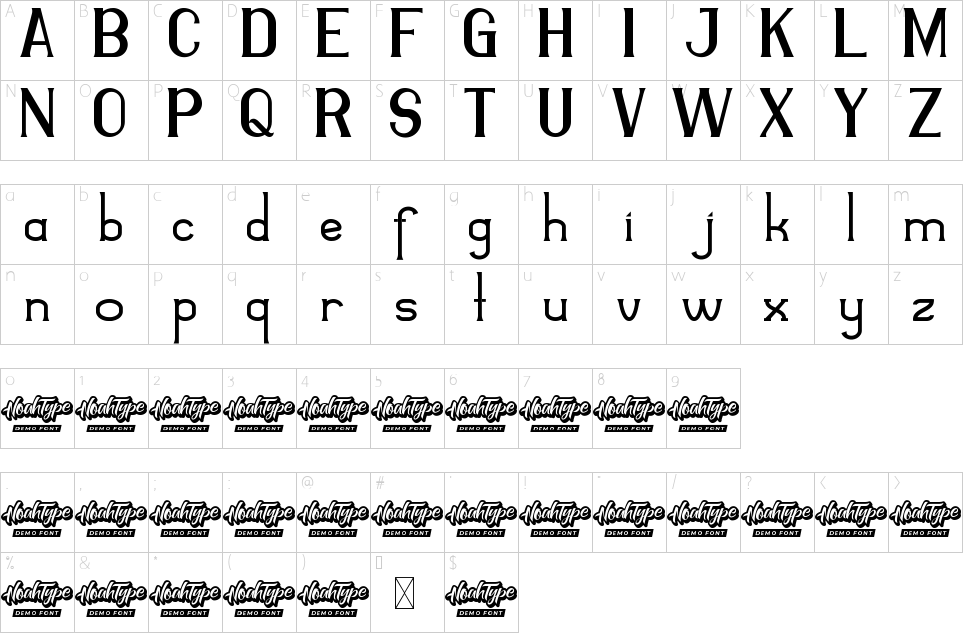
A Monster Mosha Font é uma elegante e divertida opção para quem busca um estilo único e vibrante para seus projetos. Ela foi criada pelo designer NoahType e, embora o nome não seja mencionado na descrição original, já foi baixada por 1.284 usuários. Esta fonte é perfeita para aqueles que buscam uma combinação única de seriedade e humor, sejam eles designers, profissionais de marketing ou criativos em geral. Com um design que mescla linhas fortes e traços delicados, a Monster Mosha é uma escolha adequada para qualquer tipo de projeto gráfico, desde o site do seu negócio até a capa de um livro. Se você está procurando por uma fonte que brinque com as cores e as formas, sem deixar de lado a funcionalidade e o impacto visual, a Monster Mosha é definitivamente algo que você deve considerar.